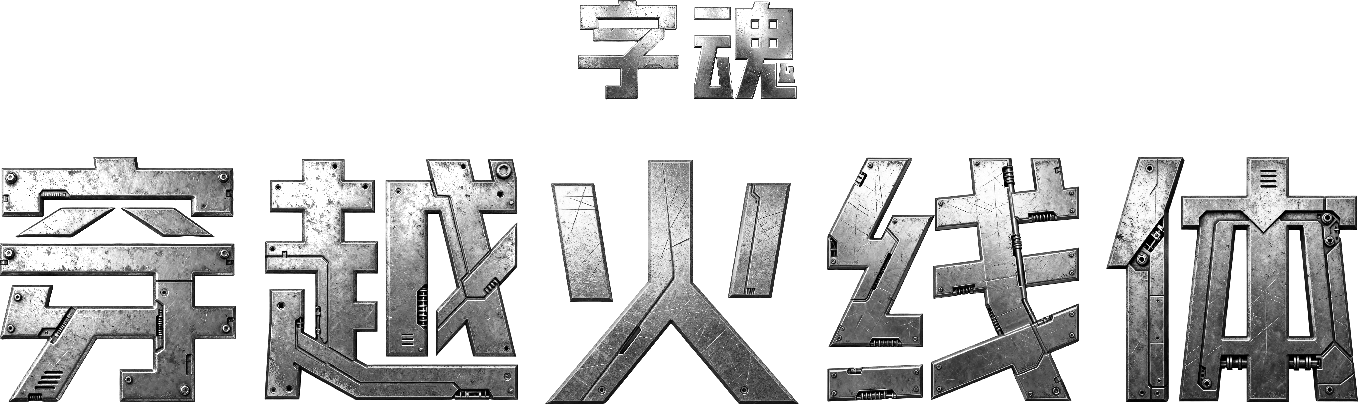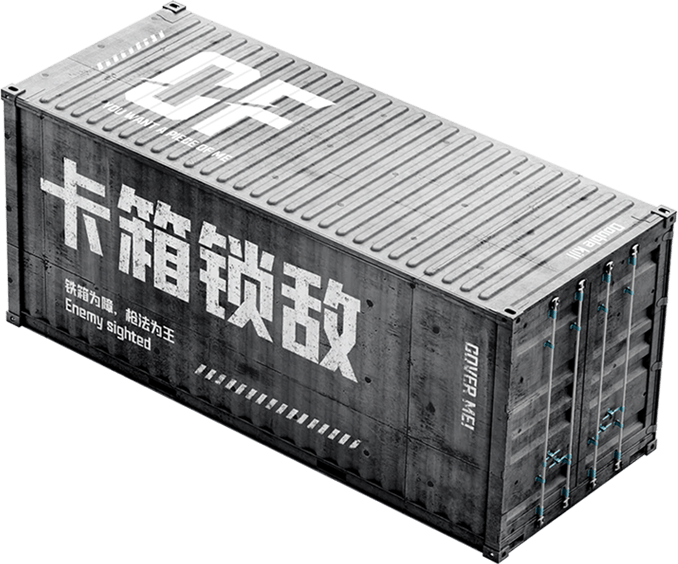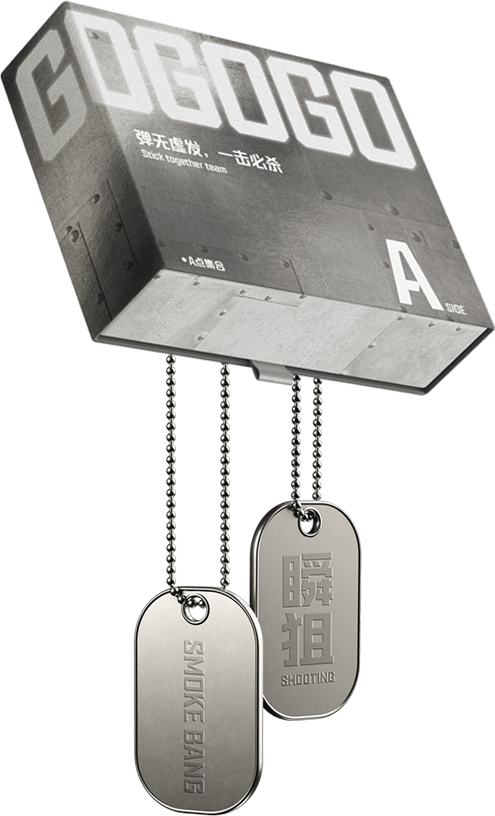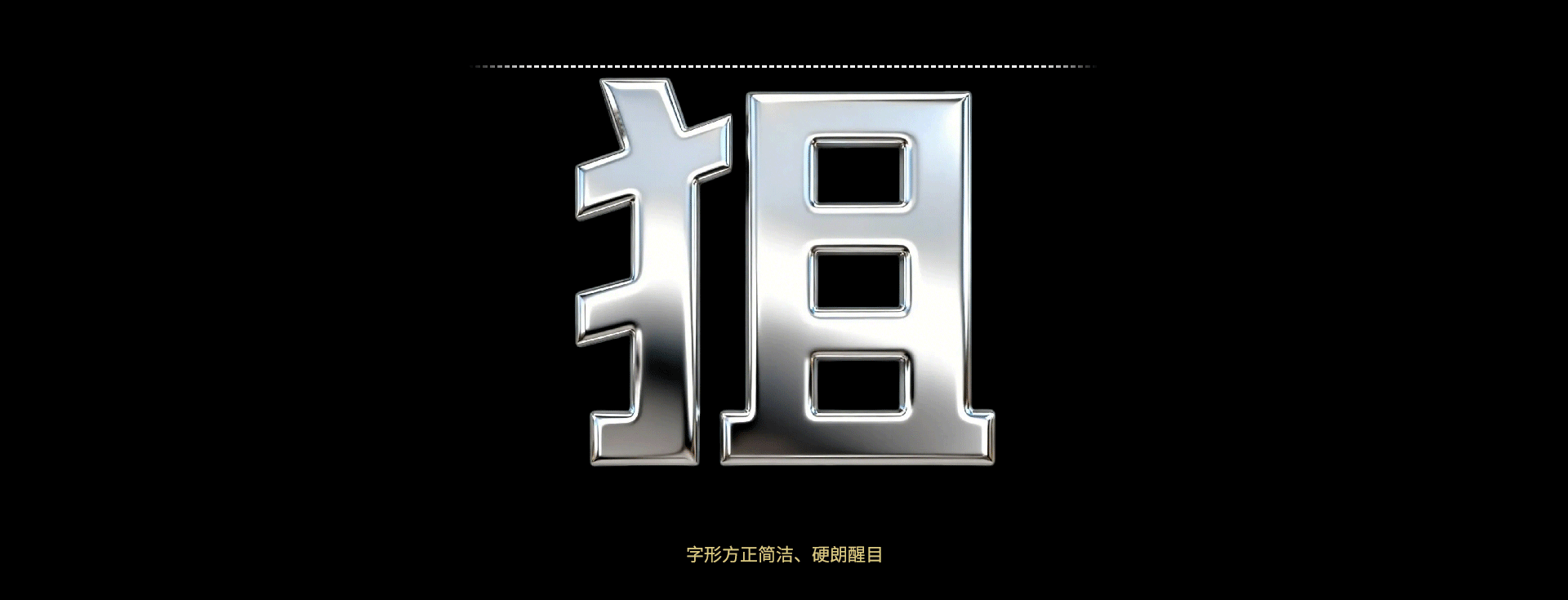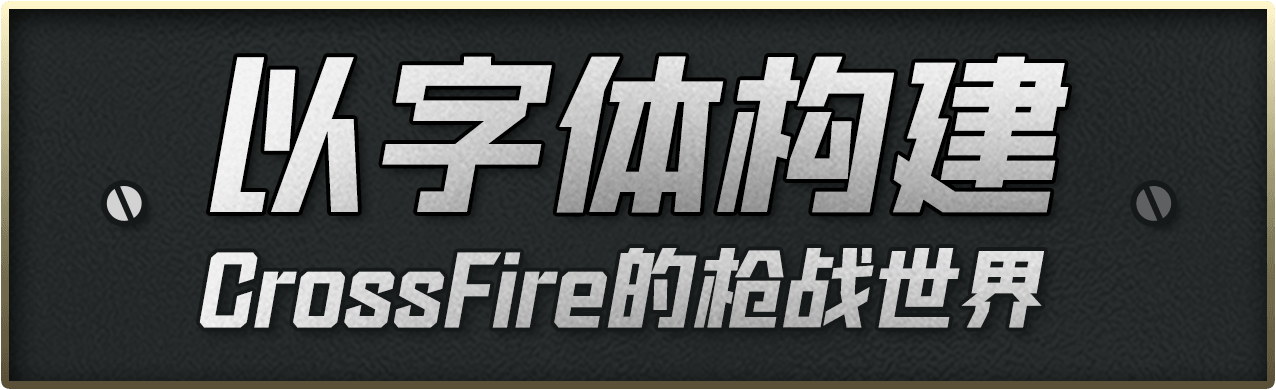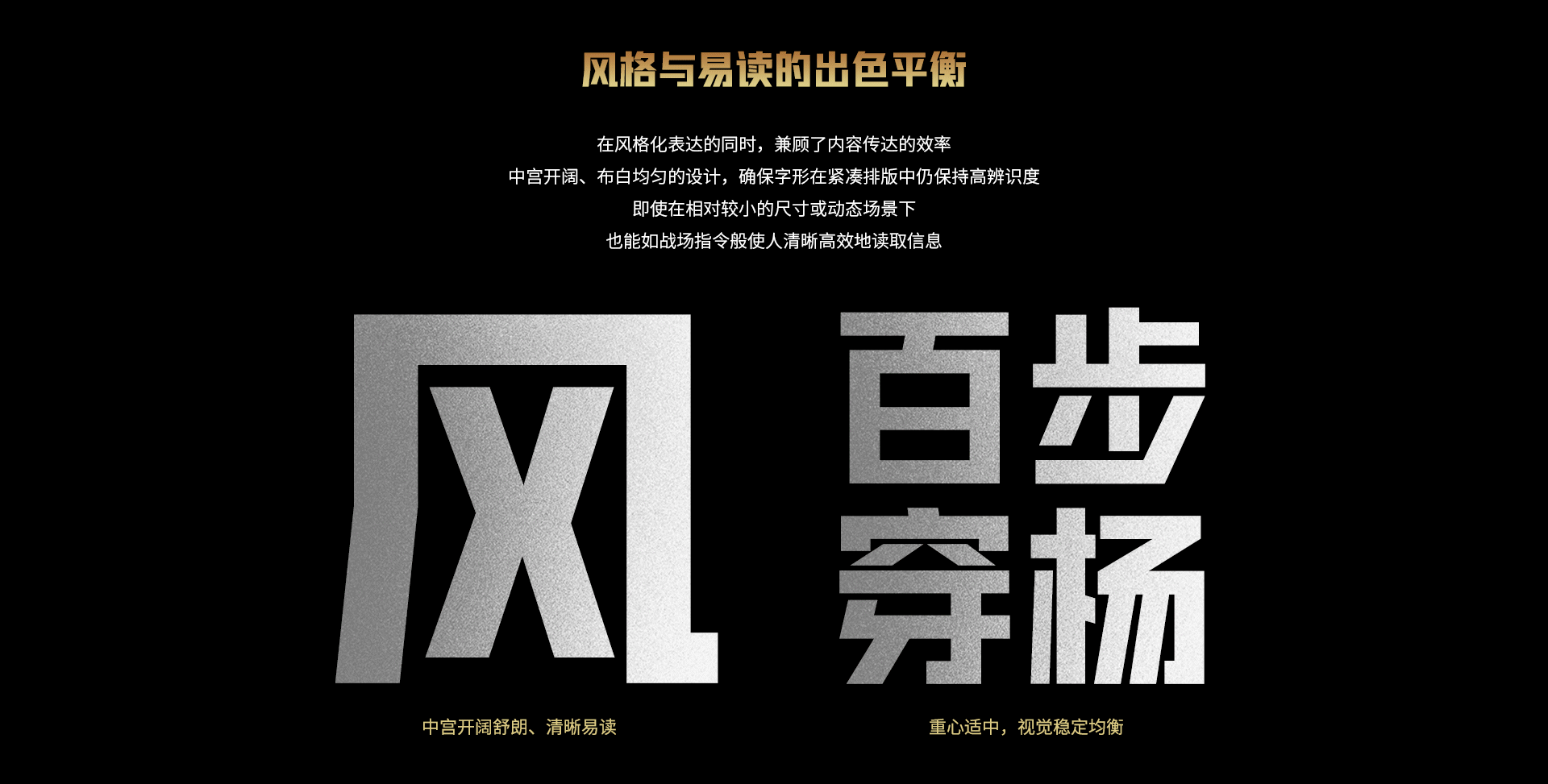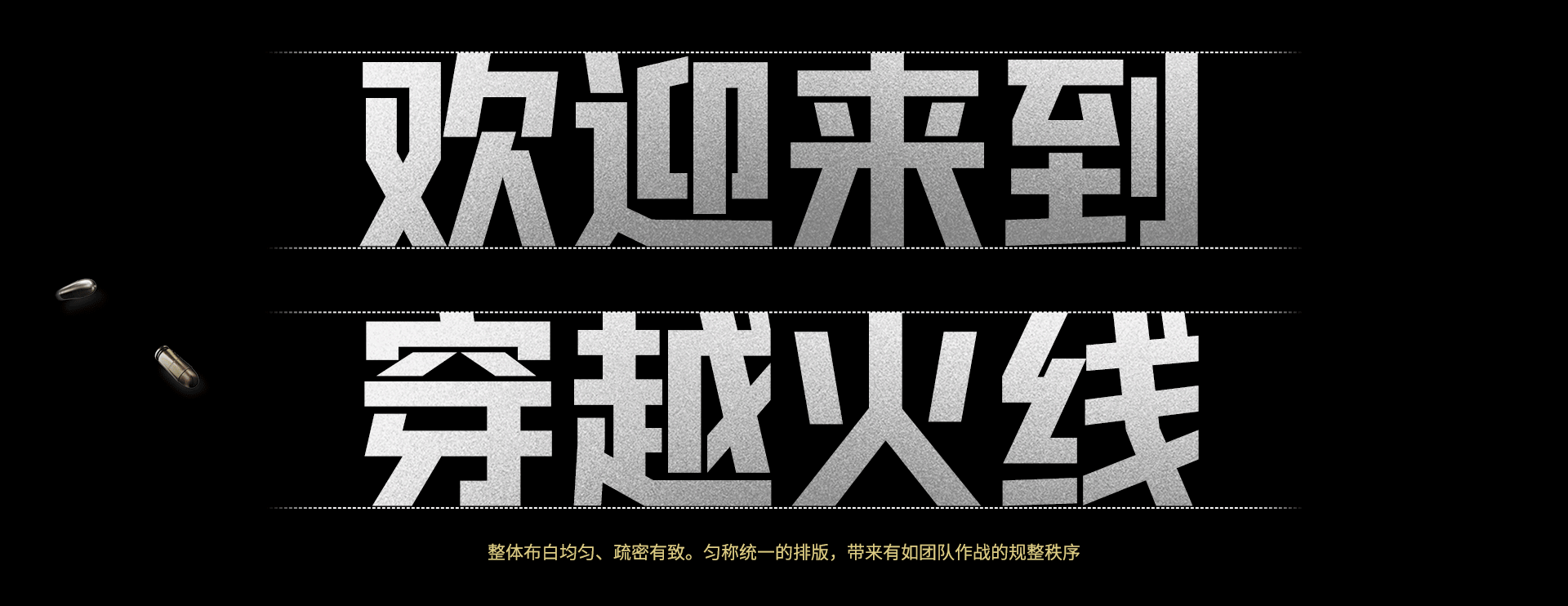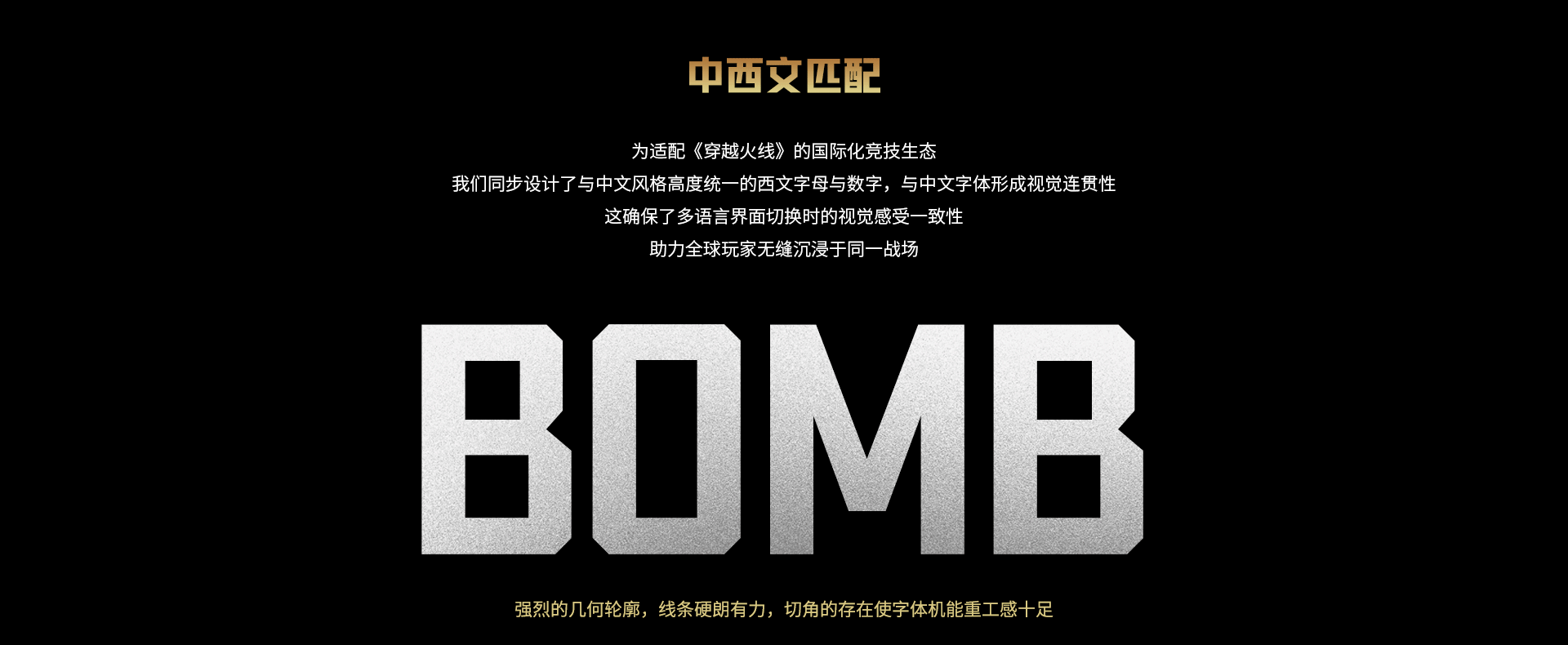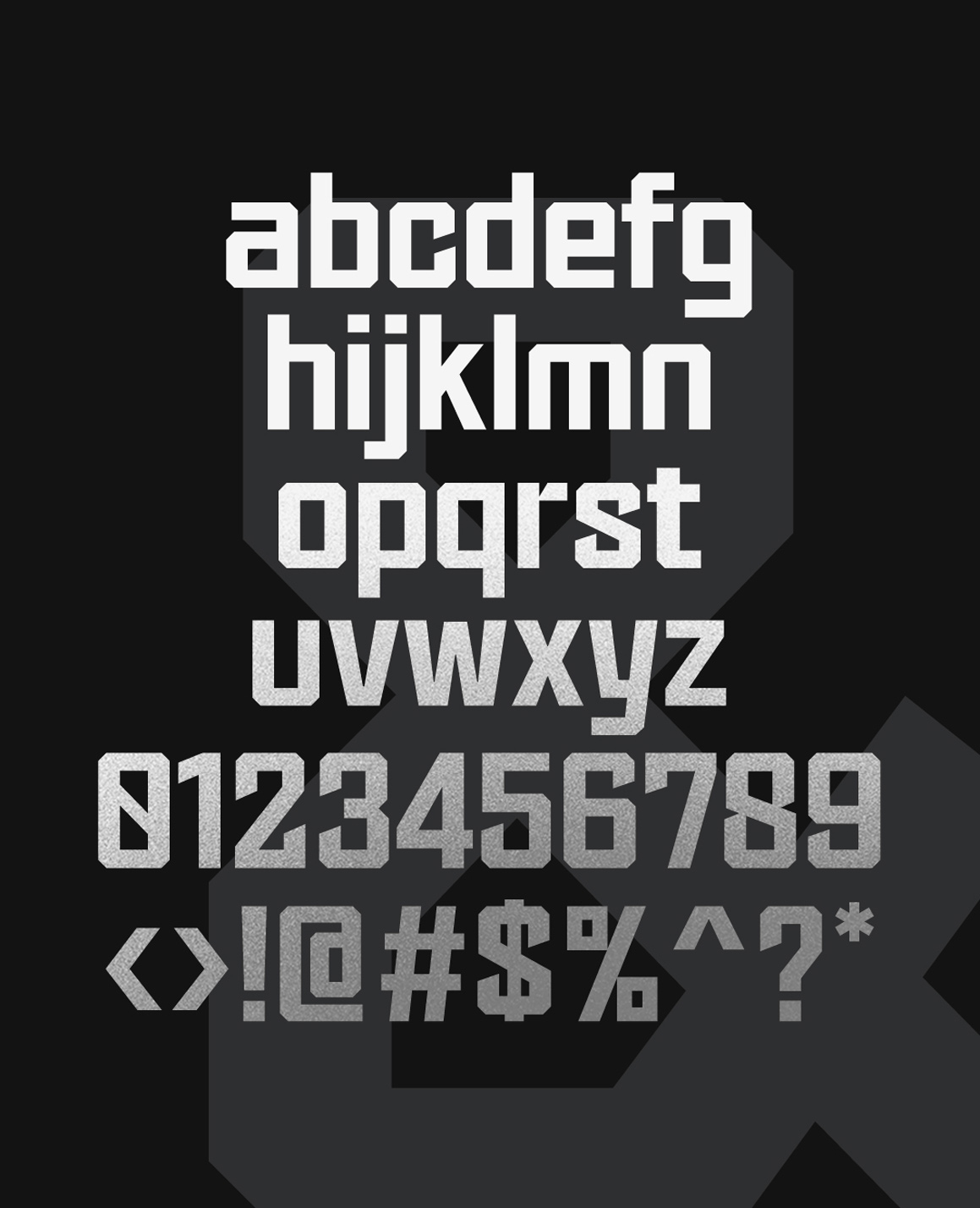
针对一个鲜明的游戏主题,字体应与其整体美术风格一脉相承
通过对应用场景的融入,创造出一个使玩家身临其境的独特世界
《穿越火线》作为一款经典射击游戏
其视觉语言需与硬核、热血的战场氛围高度契合
字魂为其量身打造的定制字体,以工业黑体为架,融军事风、科技感与竞技精神于一体
字形方正硬朗,在简洁中迸发力量,在秩序中展现锋芒
十分呼应游戏“刚毅、果决、迅捷”的战场美学
为强化视觉张力,在字体设计上刻意强化了锐角、直线与连笔的运用
并对复杂笔画进行了必要精简,传递出一气呵成、果断决绝的战斗意志
从官方网站、游戏内的击杀提示、装备名称,到广告推广、社媒内容与赛事直播
「字魂穿越火线体」能够贯穿玩家与游戏交互的全场景,为多种媒介和触点赋予高度协调的视觉语言
它不仅是信息的载体,更是沉浸感的营造者
每一个字的出现,都在强化游戏的精神内核与背景设定
为玩家创造出更沉浸的体验
字魂为《穿越火线》量身打造的定制字体,以工业黑体为骨架,融军事风、科技感与竞技精神于一体。字形方正硬朗,在简洁中迸发力量,在秩序中展现锋芒,十分呼应游戏“刚毅、果决、迅捷”的战场美学。